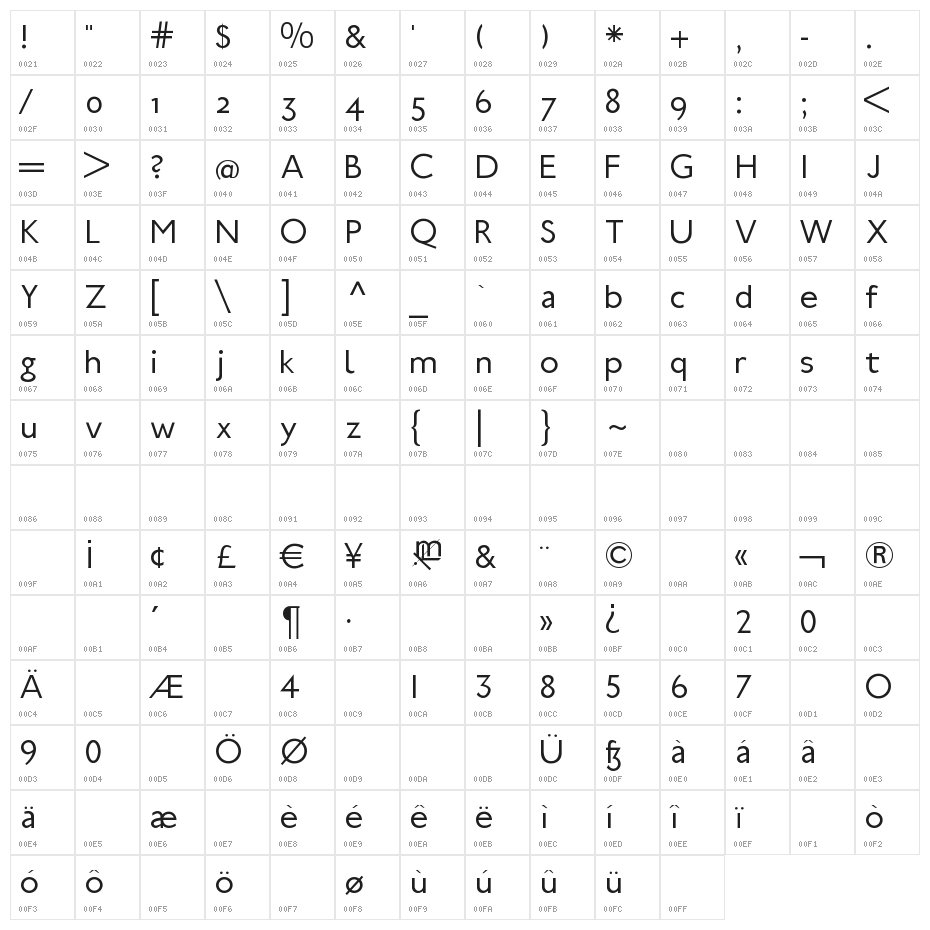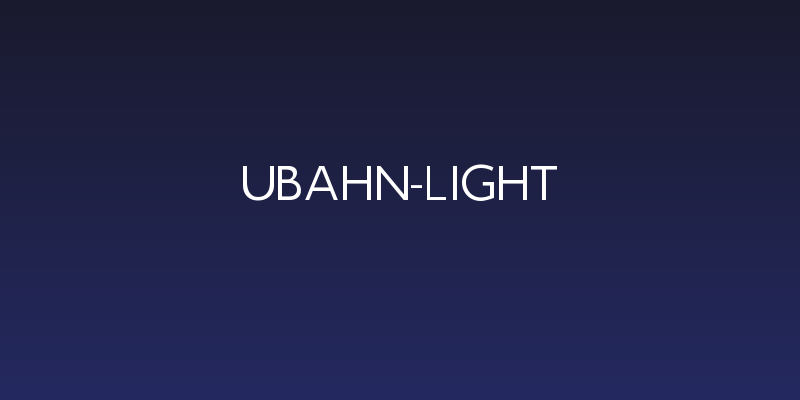
Ubahn-Light Font
| Anwendungsfall | Headlines, Body text, Logos |
| Vorgeschlagene Projekte | Ideal for branding, signage, digital interfaces, and editorial design where clarity and modernity are key. |